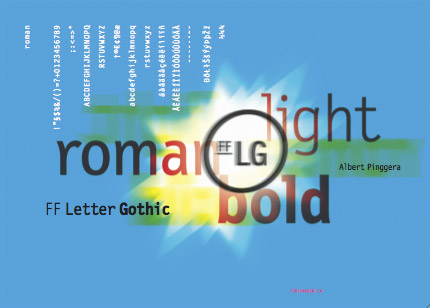
Sammelkarte: Letter Gothic de luxeVor 10 Jahren erschien die erste Fontcard-Serie: typografische
Miniaturen, die neue FontFont-Schriften begleiteten. Wegen ihrer geringen
Auflage wurden die Fontcards rasch zum Sammelobjekt. Bis Ende 1997 erschienen
100 Motive. Zum 10-jährigen Jubiläum veröffentlicht Fontblog
jetzt die schönsten Fontcards als PDF-Edition: aufwendig
![]() Um 1996 beschloss FSI FontShop International, den
Schreibmaschinen-Klassiker Letter Gothic zu überarbeiten und so zu
digitalisieren, dass die Schrift den Anforderungen des Desktop Publishing
genüge. Der italienische Designer Albert Pinggera übernahm den
Job und schuf FF Letter Gothic Text.